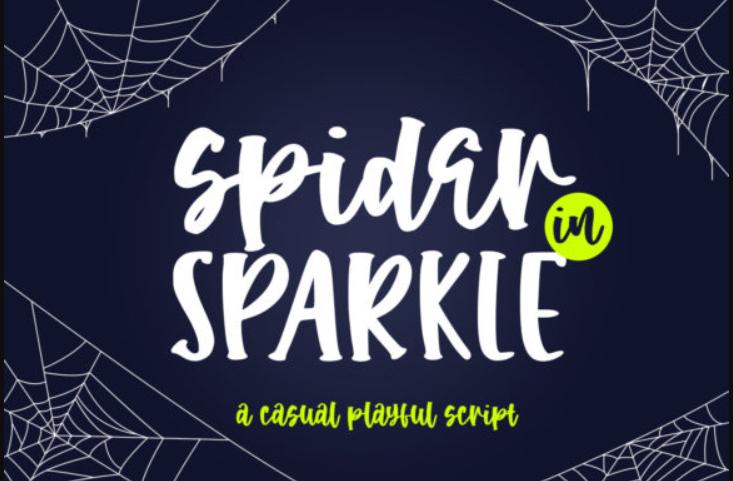
[Creativefabrica] Spider in Sparkle Font (Abodaniel)
Spider in Sparkle - это классный, непринужденный и игривый рукописный шрифт. Независимо от темы, этот шрифт станет отличным дополнением к вашей библиотеке шрифтов, так как он может улучшить любое творение.